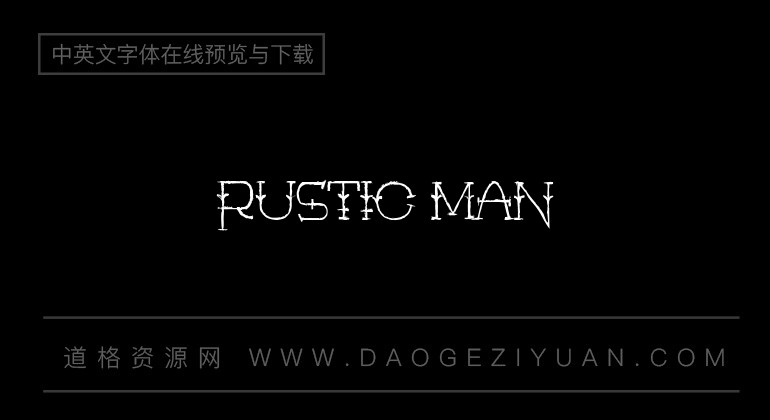
Rustic Man是一种手写风格的字体,它的特点是有着粗犷的线条和自然的笔画,让人联想到野外探险、坚毅、自由、独立等元素。 该字体由设计师Yusup Saputra创建,包含了大写字母、小写字母、数字和标点符号。Rustic Man字体的设计灵感来自于印刷时代的手写风格,如牛仔、野人和农民等人们在日常生活中使用的字体。 使用Rustic Man字体可以为设计带来独特的效果,尤其适合用于户外、冒险、野外生存、自然等主题的设计,同时也适合用于印刷品、包装、海报、标志、标签等多种设计领域。内容介绍
Rustic Man是一款非常不错的手写艺术字体,具有很好的视觉感,适合于文化类的宣传设计、商业类品牌的广告和产品包装设计以及个性化文字排版等较多场景。